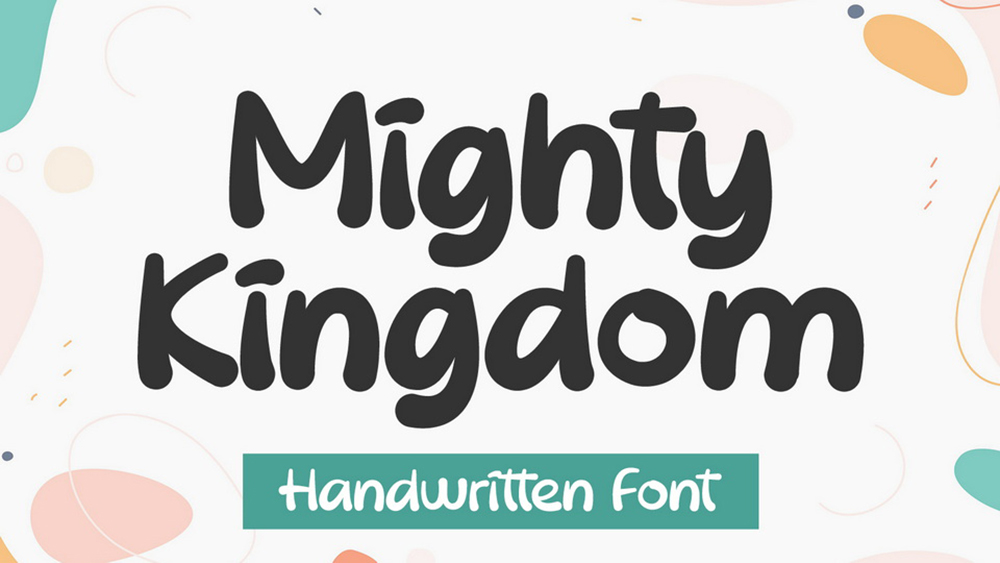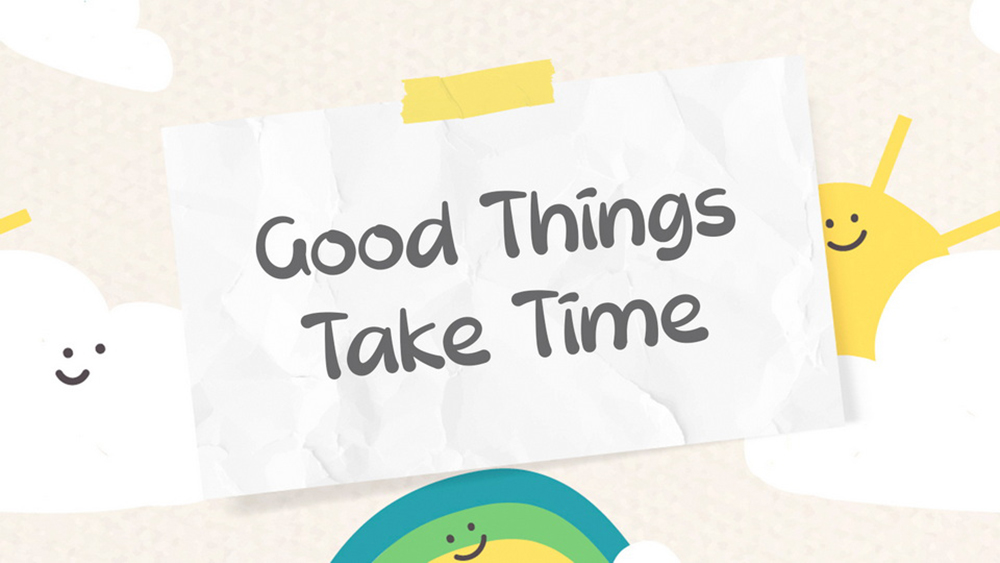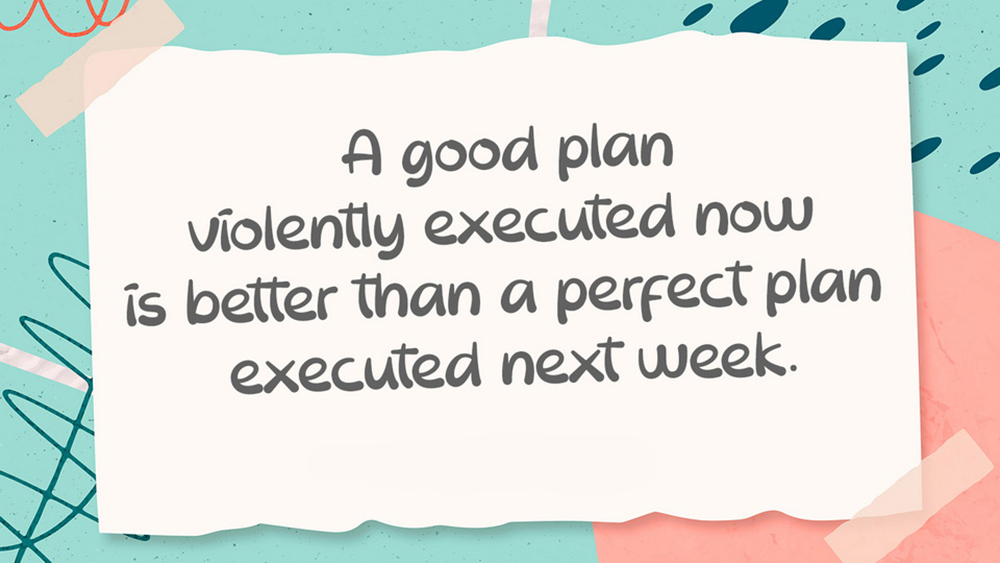
دانلود فونت انگلیسی Mighty Kingdom Font
فونت پرمیوم و انگلیسی Mighty Kingdom Font يک فونت دستنويس دوستداشتنی با ظاهری بامزه و بازيگوش است. اين فونت که کمی عجيب و غريب است، به هر يک از طرحهای شما جلوهای خاص میبخشد.
مزایای استفاده از فونت لاتین Mighty Kingdom چیست؟